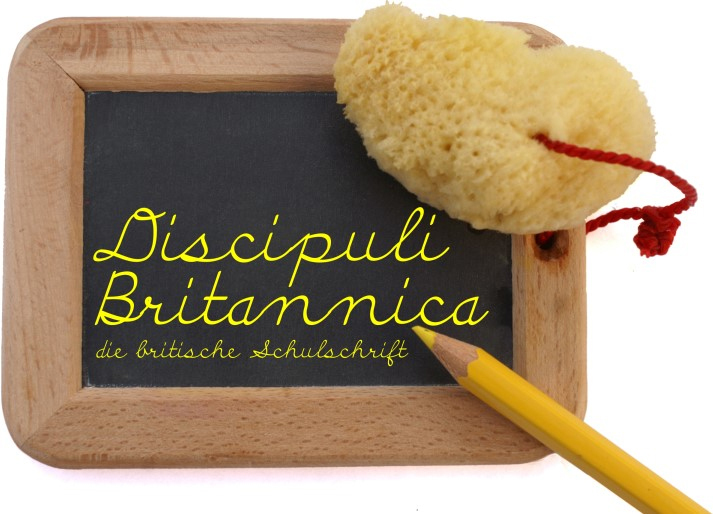
Discipuli Britannica Bold è un carattere scolastico gratuito disegnato da Peter Wiegel, plasmato con il ritmo naturale di una grafia scolastica esercitata. Lettere arrotondate, tratti collegati e curve delicatamente irregolari creano un'impressione amichevole e manoscritta, mentre le forme ampie simili a un pennino mantengono il segno sicuro e diretto.
Il suo movimento fluido conferisce un tono informale e umano a poster educativi e schede didattiche. Utilizza questo font gratuito per copertine di libri per bambini, materiali didattici museali, grafiche per eventi scolastici o packaging giocosi, dove il suo familiare stile manoscritto può ammorbidire illustrazioni e layout strutturati.